近年来,微信等社交软件的成熟,为产品的市场推广提供了更多的发展空间,互动营销强势剥离。伴随着这种营销模式,字体应用也从强势逼人的黑体宋体中细分出来,更加具有交互、更加亲切的个性字体,也逐渐占领了大片市场,如果看到比较个性的字体又不认识是什么字体呢,那么就可以通过图片字体来识别你想要的字体。
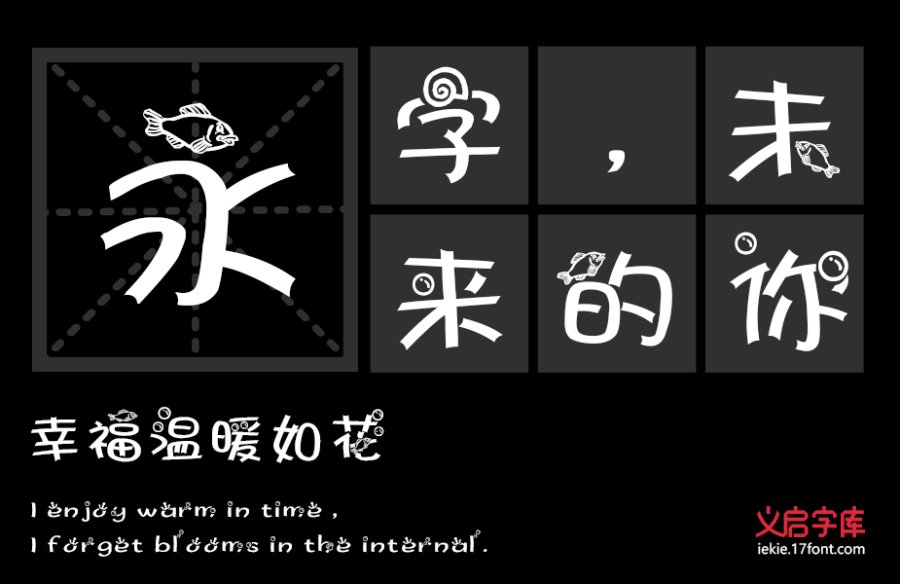
个性字体这种字体可以被广泛使用,除了手写体自带的个性使然,更重要的是与应用场景的适配性。对字体线条粗细的把握,字体重心的效果,字体的设计风格,都决定了这款字最终的应用表现。印品字体中的个性字体看起来是不是觉得这样的字体特别温暖,特有人情味儿,或可爱优雅,或呆萌粗线条。这些字体用在设计中,也会为你的作品增添不少“人情味”,给人一种亲切的感觉。
1.标题党级别
标题党级别的含义就是:作为标题字体最重要的就是“引人注目”,所以线条一定不能太细啦,粗壮的线条或者变换多端的造型,都有着强大的表现力,这让看官的眼睛,想挪都挪不开!
2.优雅小标签
小标签是最朴实无华的存在,任何地方都需要,写名字、标价包括最简单的对话,清晰又温暖。
这些字体的相对上面两个级别的稍微细一些,但也是做小标题的好手,细线条更精致,徐老师的精致的静蕾体可谓是红了数十年。